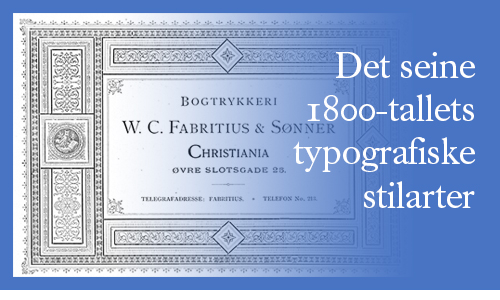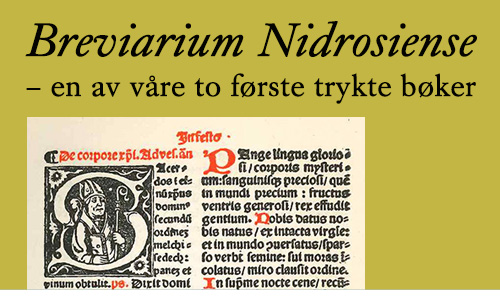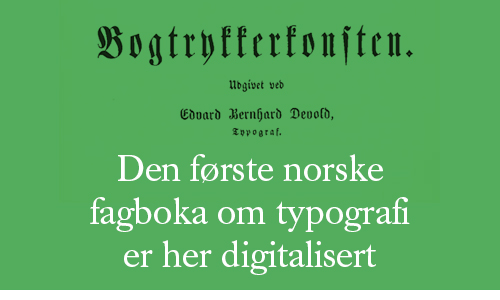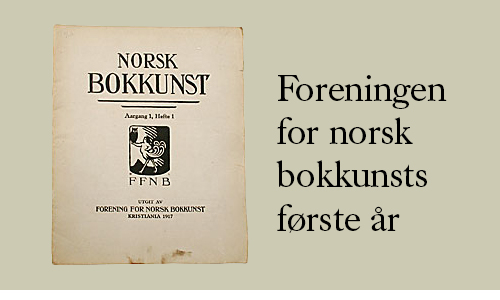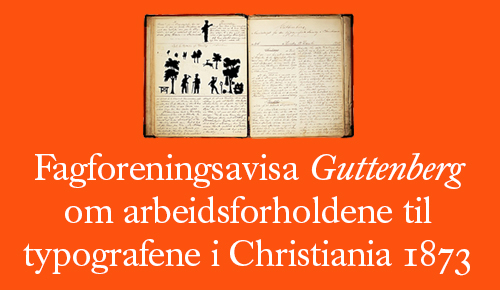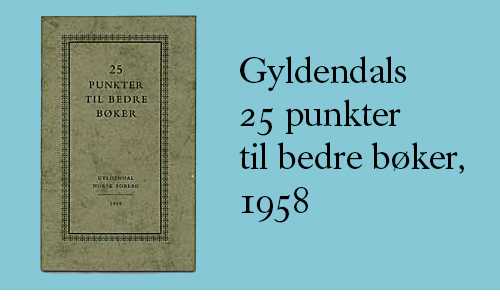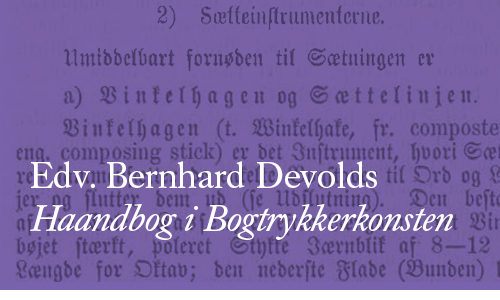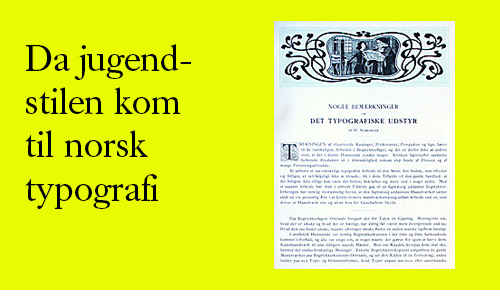
Kilder til norsk grafisk historie
Jeg vil her legge ut dokumenter fra norsk grafisk historie.
Foreningen for norsk bokkunst
Foreningen for norsk bokkunst ble stiftet i 1900 av bokelskere, kunstnere og boktrykkere i Christiania. Den fikk begrenset betydning i norsk bokverden. Her er en historie om dens første år, skrevet av overbibliotekar Wilhelm Munthe i 1943. Mer ->
Gyldendals 25 punkter til bedre bøker
I 1958 utga Gyldendal et hefte med de typografiske kravene de stilte til boktrykkerne. Det er i dag interessant å studere disse og sammenligne med dagens typografiske standarder. Mer ->
Da jugendstilen kom til norsk typografi
Den framstående boktrykker Hermann Scheibler ved Oslo-trykkeriet Fabritius diskuterte allerede i 1903 jugendstilens bakgrunn og karakter, slik den kom til uttrykk i boktrykket. Mer ->
Norges første boktrykker
Etter at Tyge Nielssøn kom fra Danmark til Christiania i 1643 for å trykke et religiøst verk, ble det uenighet om avtalen, og han mistet pressa si etter en dom. Denne artikkelen fra 300-års jubileet forteller denne historien og gir svar på hvor han så ble av. Mer ->
Typografiforfatteren E. B. Devold
Bergen-typografen Edvard Bernhard Devold utga den første norske typografi-læreboka i 1863, ei bok som har vært glemt i over hundre år. Blant beskrivelser av håndsatsens teknikk og regler finner man mye interessant. Mer ->
Moderne typografi og trykk
Boktrykker Arthur Nelson, som var den som først interesserte seg for «den nye typografien» i Norge, skrev i 1929 den første store, begrunnede artikkel til forsvar for den nye retning. Mer ->
En nordisk skrift
Rolf Hjorth Johansen innledet i 1936 om muligheten for å komme fram til en nordisk skrifttype. Artikkelen inneholder også en vurdering av de smaksendringene som hadde funnet sted fra 1. verdenskrig fram til 1936. Mer ->
Illustrasjon av Hjorth Johansen
Norges-alfabetet
I 1990 ble et visuelt profileringsprogram for Norge tatt i bruk. Basert på en omfattende analyse av Norge og det norske, ble det utarbeidet et logoalfabet. Dette vakte debatt i designmiljøet, og møtte stor motstand. Mer ->
Illustrasjon av Norges-alfabetet
Norsk boktrykk kalender
Den typografiske forening i Kristiania startet i 1918 utgivelsen av en faglig årbok, som fram til sin siste årgang i 1974 inneholdt viktige bidrag til utviklingen av de grafiske fagene i Norge. Også for dagens leser inneholder de mye interessant. Mer ->
Kirste om aksidenser
Boktrykker Max Rich. Kirste har hatt stor betydning for det norske grafiske fagmiljøet. Hans «Håndbok for unge settere, aksidenssats» (1935) formidlet «den nye typografiens» prinsipper for arbeidet med forretningstrykksaker, reklame osv. Mer ->